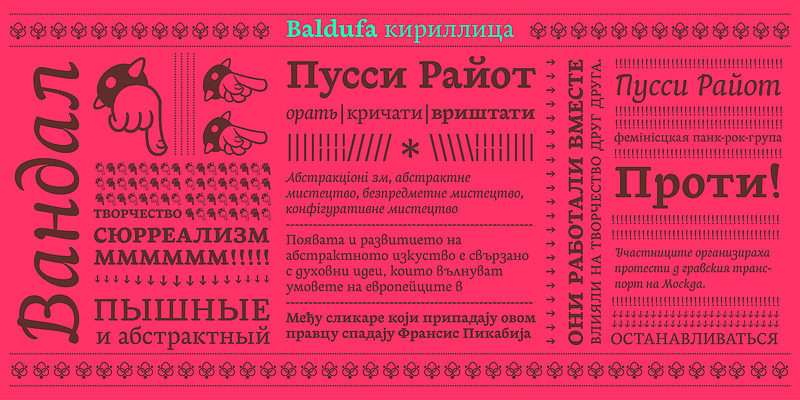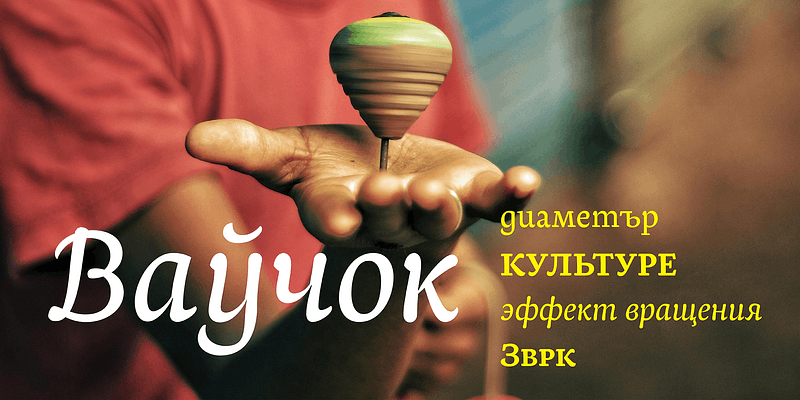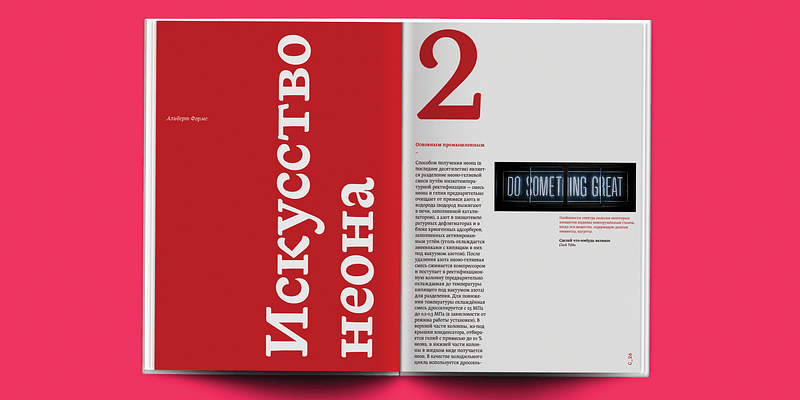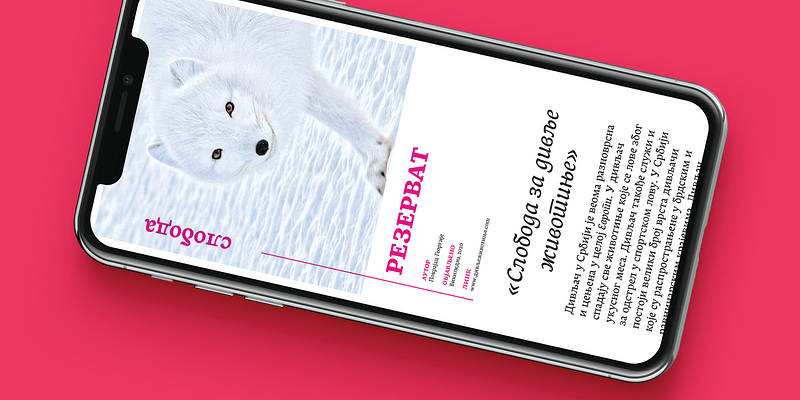
Baldufa est une police destinée aux livres, aux catalogues et aux petites publications dans le domaine culturel (art, design, etc.). Elle est conçue pour être utilisée dans des publications multilingues (arabe, latin, cyrillique et grec), mais chacune des écritures fonctionne bien individuellement. La police est utilisée naturellement pour des contenus éditoriaux pour lesquels les utilisateurs recherchent une valeur ajoutée plutôt qu’une simple compilation d’informations, un objet que l’on se plaît à conserver. La famille de polices offre une large gamme d’épaisseurs pour couvrir tous les besoins en matière de design d’ouvrages.
Le dessin de la police explore la structure de la lettre, rompant avec certaines manières conventionnelles de répartir le contraste, les tiges ou les empattements. L’anatomie des lettres abandonne le mouvement cohérent de la plume pour introduire des formes plus expressives et plus personnelles. Le design apporte du mouvement, de la répétition et de l’expressivité au texte, invitant le lecteur à lire le contenu.